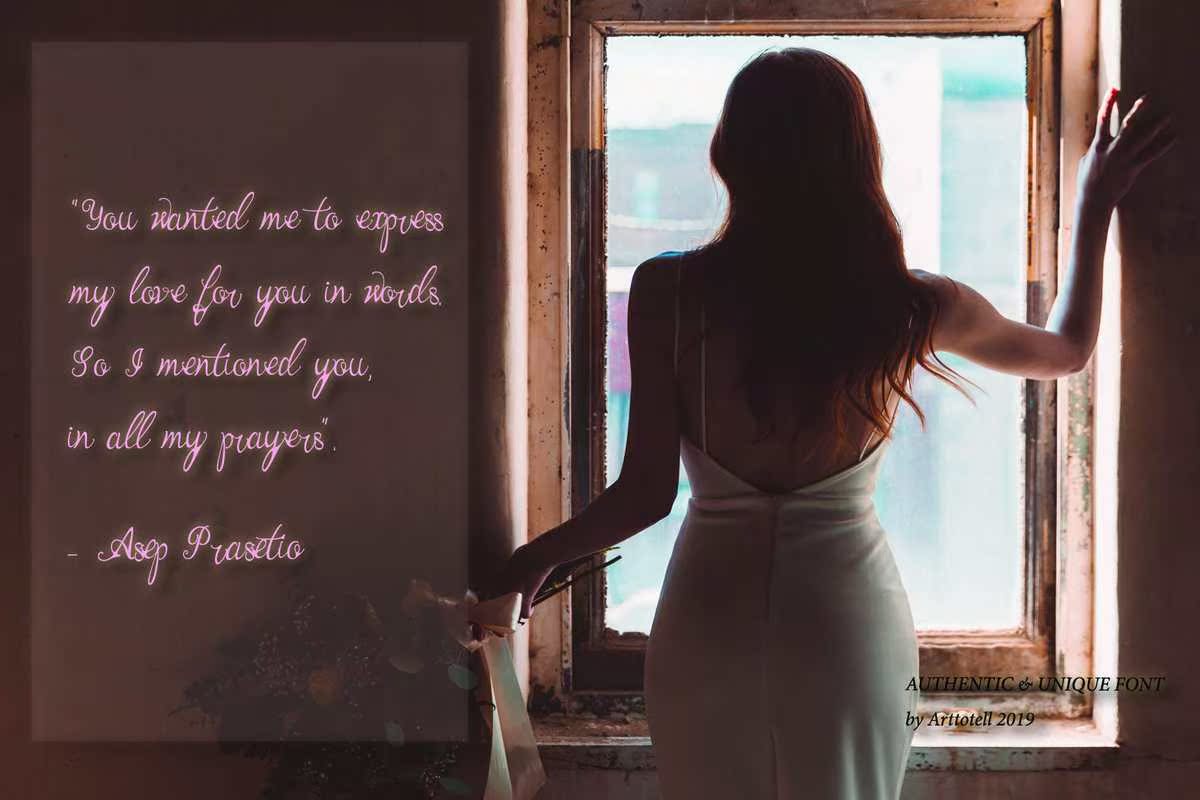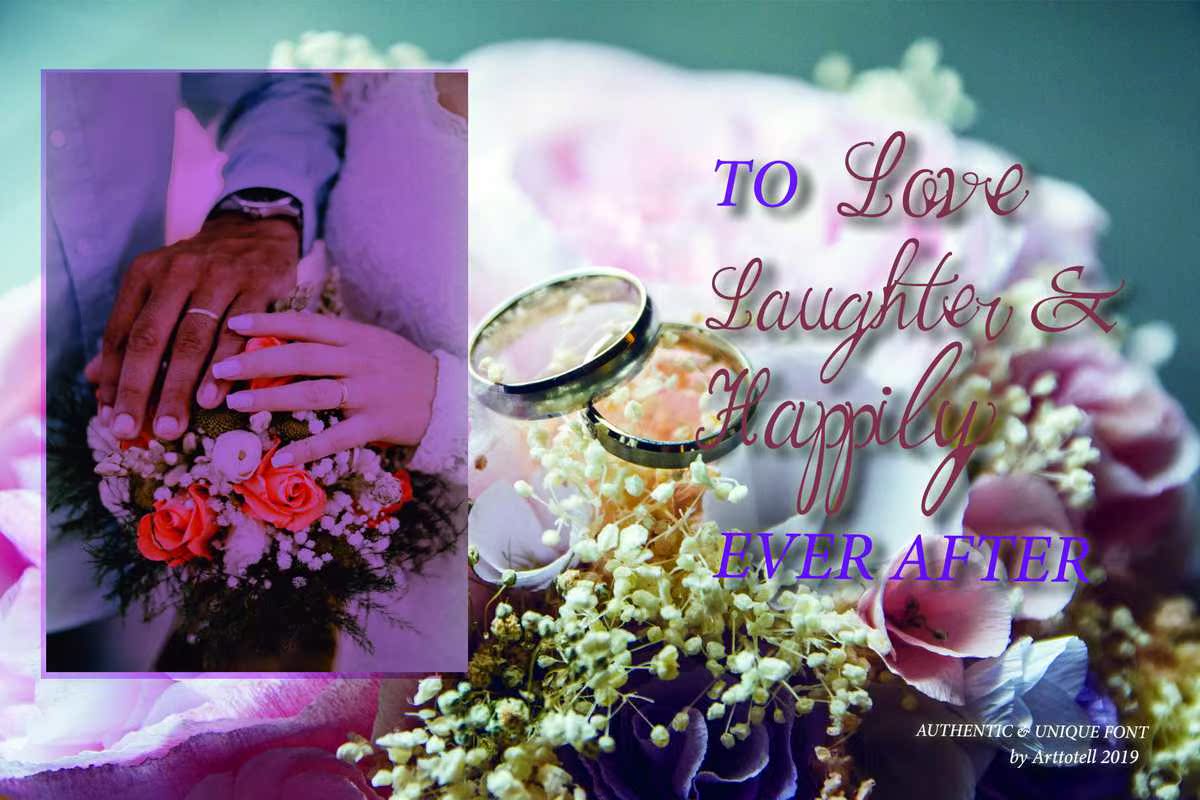
BernadineScriptf字体为自然、独特、签名和柱式手写字体,带有Anaturaland精美的字体。它可以用于各种设计项目,并且非常方便。BernadineScriptf字体包括大写、小写、标准标点符号和数字。BernadineScriptf字体为自然、独特、,签名和柱式手写字体,带有Anaturaland精美的字体手册。它可以在设计项目的任意范围内使用,并且非常方便。Bernadinescriptf内容包括大写、小写、标准标点符号和数字